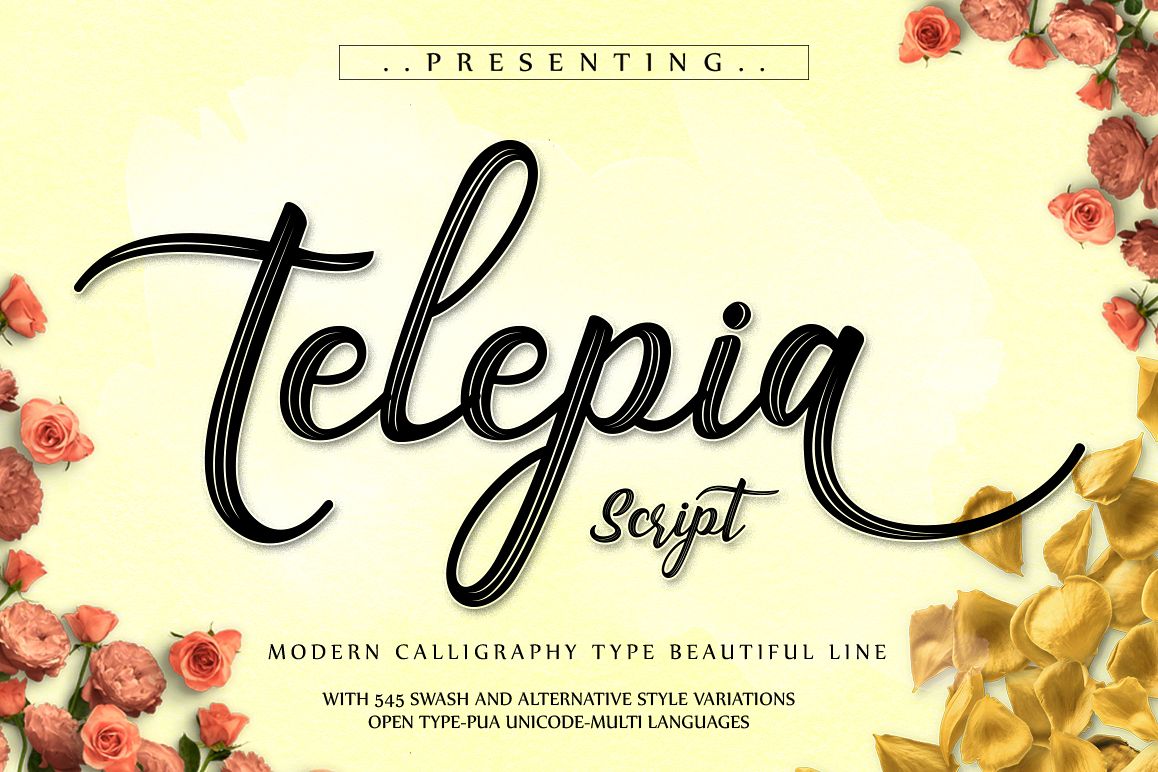
Dan mesin terbang yang terdiri dari 546 swash gaya dan menawan Dan garis-garis di font. Font brisi garis lurus yang indah Font disediakan dalam format TTF & OTF. Saya sarankan untuk memasang file TTF, dan OTF hanya jika perlu. Tidak ada perbedaan fungsi dengan format baik. Font termasuk dukungan multibahasa untuk bahasa berikut; Nah, hampir mencakup semuanya,  saya sangat berharap bisa menikmatinya dan jangan ragu untuk  menyampaikan pesan jika ada masalah atau pertanyaan :) Telepia Web Font Scripts (eot, svg, woff , Woff2) Jika Anda tidak memiliki program yang mendukung fitur OpenType seperti Adobe Illustrator dan CorelDraw X Versions, Anda dapat mengakses semua mesin terbang alternatif menggunakan Font Book (Mac) atau Character Map (Windows). Untuk digunakan dalam kata kantor , Anda bisa membaca artikel berikut ini. Http: //www.magpiepaperworks.com/blog/using-opentype-fonts-in-microsoft-word/ Untuk Mengakses Karakter Alternatif Klik Tautan di bawah ini: Adobe illustrator CS https://www.youtube .com / watch? V = geL0Ye02Ryk Bagaimana  cara mengakses alternatif di ilustrator Adobe CC https://www.youtube.com/watch?v=V25yiUh8BcE Bagaimana  cara mengakses alternatif di Ms Word https: //www.youtube.com/watch? V = HxkhZiCuwEw Bagaimana  cara mengakses alternatif di Coreldraw X7 https://www.youtube.com/watch?v=UBVsufJjons Bagaimana cara mengakses alternatif di Adobe Photoshop CC https://www.youtube.com / watch? V = BYKXl58AdNY Cara mengakses alternatif di Indesign CS https://www.youtube.com/watch?v=HgZTCxKG14Q  Cara mengakses alternatif di perangkat lunak lain https: // fontbundles.